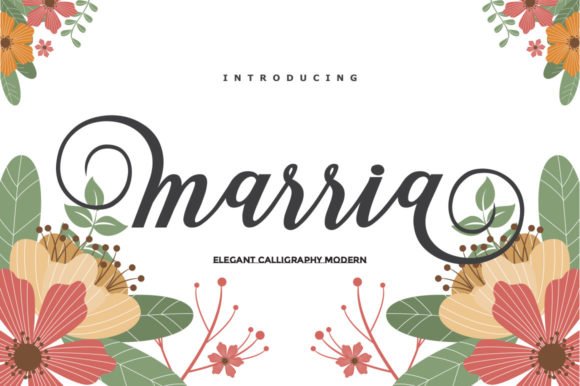
Marria Script Font
Marria Script Font – خط أنيق ومميز لمشاريعك الإبداعية
خط Marria Script هو خط مكتوب باليد يتميز بتصميم أنيق وانسيابي يمنح لمشاريعك لمسة من الفخامة والإبداع. يجمع بين الأسلوب الكلاسيكي والحديث، مما يجعله خيارًا مثاليًا لمجموعة متنوعة من الاستخدامات، مثل:
تصميم الشعارات والهوية البصرية
الدعوات وبطاقات التهنئة
تصميمات وسائل التواصل الاجتماعي
أغلفة الكتب والمجلات
المواد التسويقية والإعلانية
يأتي الخط بجودة عالية مع دعم متعدد للغات، مما يضمن لك تجربة استخدام سلسة ومتنوعة في جميع مشاريعك. احصل على Marria Script Font اليوم وأضف لمسة إبداعية راقية إلى تصاميمك!